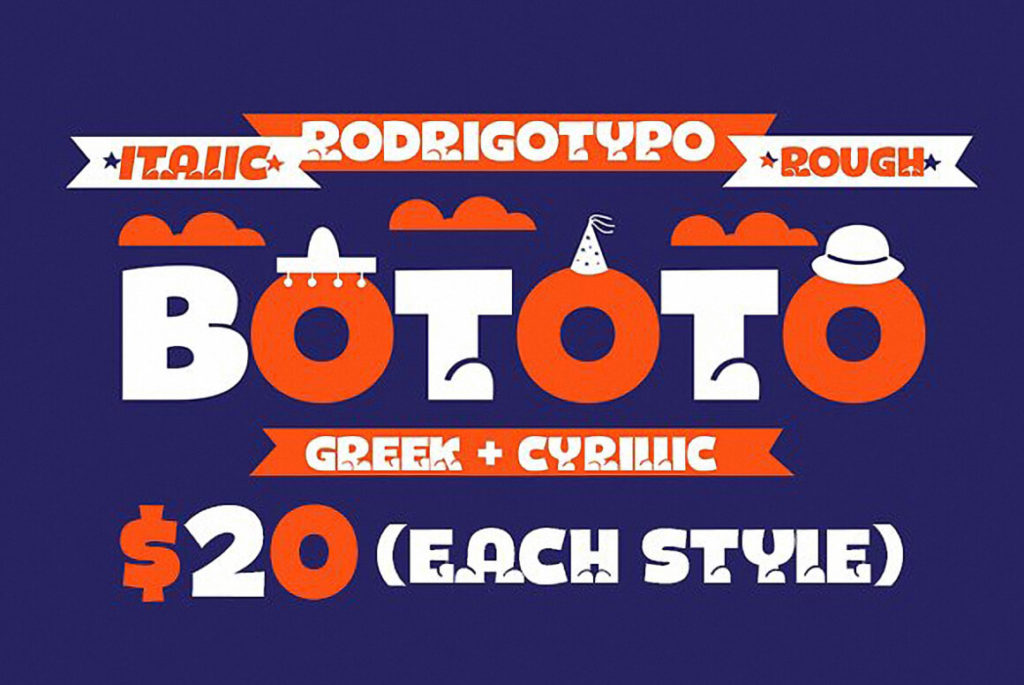
это современный акцидентный гротеск с игривым и динамичным характером, созданный студией RodrigoTypo в 2023 году. Шрифт отличается выразительными формами букв, напоминающими следы или «ноги», что придает ему уникальную динамику. Он идеально адаптирован для кириллических текстов и поддерживает латиницу, а также греческий алфавит. Благодаря своей игривости и высокой читаемости, шрифт отлично подходит для детских проектов, креативной рекламы и веб-дизайна. Вы можете **скачать бесплатно** кириллическую версию шрифта прямо сейчас, чтобы добавить индивидуальности своим проектам